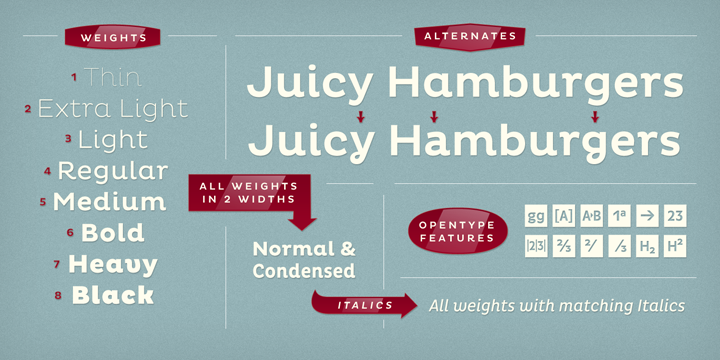
Font für eine iOS-App zum Lesenlernen
wir bauen gerade eine App fürs iPad, mit der Kinder längere Buchtexte zum Lesen dargestellt werden sollen. Ich suche eine Schrifttype, die
1. standardmäßig auf iOS (oder frei) verfügbar ist und
2. Serifen hat (ich hab mal gehört, das soll für das Lesenlernen besser sein als serifenlose Schriften, da z.B. p und b und d besser auseinander gehalten werden können) und
3. die einigermaßen typisch für Bücher ist (gewohnt) und
4. ein kleines g enthält, bei dem der obere und der untere Teil auf der rechten Seite verbunden sind (wie in den Schreibschriften; ich denke das wäre besser).
GIbt's das? Ich habe länger gesucht, aber Georgia, Palatino oder Times New Roman haben dieses seltsame kleine g.
… ein kleines g enthält, bei dem der obere und der untere Teil auf der rechten Seite verbunden sind (wie in den Schreibschriften; ich denke das wäre besser).
Das habe ich noch nicht ganz verstanden. Meinst Du so etwas wie die g-Alternative der Pluto?
Danke für den Hinweis und die Nachfrage. In Times usw. ist das kleine g auf der linken Seite verbunden. Das hat mich als Kind immer irritiert. Ich meine also nur die Verbindung auf der rechten Seite, keine speziellen Lösungen wie in Pluto.
wir bauen gerade eine App fürs iPad
Serifen sind gut, aber das mit den für Lesenlerner vermeintlich einfacheren Buchstabenformen ist Quatsch. Die komplexen Formen lernen Kinder im Handumdrehen, wenn sie sie nicht schon kennen (was wahrscheinlich ist, da sie die überall sehen). Wenn überhaupt, sind die »einfacheren« Formen problematischer, weil sich das einstöckige a eben sehr viel einfacher mit dem o verwechseln lässt, und das einfache g sieht für Dyslexiker evtl. auch aus viel eine 9. Dagegen sind a und g wunderbar eindeutig.
Aber es kann gut sein, dass du bei Verwendung der eindeutigeren Formen Probleme mit Lehrern (die es nicht besser wissen) bekommst. Wenn es also unbedingt eine Serifen-Schrift mit den einfachen Formen sein soll, könnte ich noch die Cormorant Infant anbieten, die ist im 2. Beispiel zu sehen.
Danke für den Hinweis und die Nachfrage. In Times usw. ist das kleine g auf der linken Seite verbunden. Das hat mich als Kind immer irritiert.
Diese Variante des g lässt sich nur bewegungssparsam und in einem Zug schreiben, indem man den Stift etwas oberhalb der Grundlinie und auf der linken Seite der gedachten Form ansetzt und das obere Oval im Uhrzeigersinn schreibt, glaube ich. Die Schreibbewegung ist komplexer als beim Schreibschrift-g. Außerdem lässt sich das dreistöckige Druckschrift-g nicht mit dem nächsten Buchstaben verbinden. Aber von der Schreibbarkeit lässt sich nicht auf die Lesbarkeit schließen. Zumindest in Lesegrößen dominieren die beiden übereinander liegenden Ovale meiner Meinung nach den Ansatzpunkt für das untere Oval sehr stark. Kann es sein, dass das g angefangen hat, dich zu irritieren, als du bereits lesen und schreiben konntest? Das kann ja trotzdem im Kindesalter passiert sein. Ich selbst habe vor ein paar Jahren zum ersten Mal versucht, ein dreistöckiges Druckschrift-g aus dem Gedächnis zu zeichnen und war zum ersten Mal irritiert, weil der Übergang zum unteren Oval an der linken Seite des oberen Ovals ansetzt. Tatsächlich konnte ich es zuerst gar nicht zeichnen, ohne es mir anzuschauen.
Hier auf dem Forum hat sich kürzlich jemand nach Druckschriften erkundigt, die ein Fragezeichen enthalten, das einem gespiegelten S ähnelt. Seiner Ansicht nach ist das gespiegelte S die natürlichere Form des Fragezeichens. Und davon war er auch nicht abzubringen. Der Punkt ist: Persönliche Lese- und Schreiberfahrungen zu verallgemeinern, ist meiner Meinung nach heikel. Die Formen der klassischen Druckschriften und die der Schreibschriften haben sich bewährt. Kindgerechte (oder besser: menschengerechte) Druckschriften sind eher die, bei denen keine Verwechslungsgefahr zwischen I, l und 1 besteht, keine zwischen O und 0, Schriften, bei denen das p kein genau gespiegeltes q ist, das b kein genau gespiegeltes d u. s. w.
Edit: p und q bzw. b und d sind in dem Zusammenhang keine guten Beispiele. Ich schätze, dass die Abweichungen von der Spiegelbildlichkeit eher wichtig für den Rhythmus der Schrift sind. Denn die Orientierung dieser Zeichen dominiert die Feinheiten so stark wie die beiden übereinander liegenden Ovale des dreistöckigen g den Ansatzpunkt des zweiten Stockwerks dominieren.